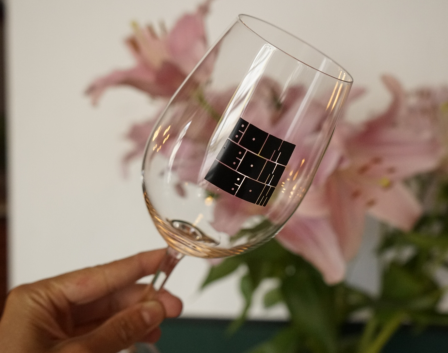
Yield Guild Games
Yield Guild Games a réinventé son identité graphique pour permettre à sa communauté de créer et d'enrichir un univers visuel dynamique et modulaire
Yield Guild Games (YGG) est une organisation autonome décentralisée (DAO) qui investit dans les NFTs que l’on utilise dans les mondes virtuels et les jeux basés sur la blockchain. Au travers du jeu vidéo, son objectif est de créer la plus grande économie virtuelle du monde.
Pionnière depuis 2018 du « Play to earn », Yield Guild Games est aussi la première et la plus grande guilde de jeu web3 au monde, dans laquelle les joueurs peuvent s’épanouir en trouvant leur communauté, en découvrant de nouveaux jeux, en s’affrontant et en évoluant dans leur pratique en collectant de multiples récompenses.
YGG nous a approchés en 2022 dans le but de repenser intégralement leur identité graphique. Notre proposition visuelle se veut riche et 100% modulaire, laissant in fine la possibilité à tous les membres de la communauté la possibilité de s’approprier tous les éléments du branding pour l’enrichir de façon autonome. Ainsi, le nouveau logo typographique, 100% custom, est une composition basée sur 18 éléments géométriques, qui, par assemblage, permettent de former un alphabet complet, se transformant en caractère de titrage, le YGG Display Mono. Cette grille de construction et ces éléments se déclinent en une famille de ‘runes’, des créatures graphiques qui prennent vie et se propagent dans tout l’univers YGG. La communauté peut créer ses propres runes, et enrichir le territoire visuel à l’infini. Les guidelines graphiques s’agrémentent de compositions visuelles diverses, statiques ou en mouvement, et d’une palette colorimétrique néon.
Notre proposition a été partiellement retenue ; les équipes de YGG ont adapté notre principe graphique sur une identité visuelle réalisée en interne.